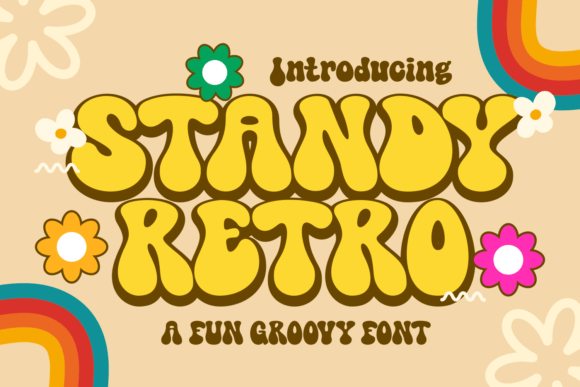
Standy Retro Font – استرجع سحر الماضي بأسلوب عصري!
استمتع بتصميم فريد يعيد إحياء جمال الخطوط الكلاسيكية مع Standy Retro Font، خط يجمع بين الأناقة واللمسة العتيقة ليناسب مختلف الاستخدامات الإبداعية. يتميز هذا الخط بحروفه الجذابة التي تعكس روح التصميمات القديمة مع لمسات حديثة، مما يجعله مثالياً للمشاريع التي تحتاج إلى طابع فني مميز.
???? مثالي لـ:
✔ تصاميم العلامات التجارية والشعارات
✔ أغلفة الكتب والمجلات
✔ المنتجات الرقمية والمطبوعات
✔ التصاميم الإعلانية والملصقات
أضف لمسة من الإبداع والحنين إلى تصاميمك مع Standy Retro Font!